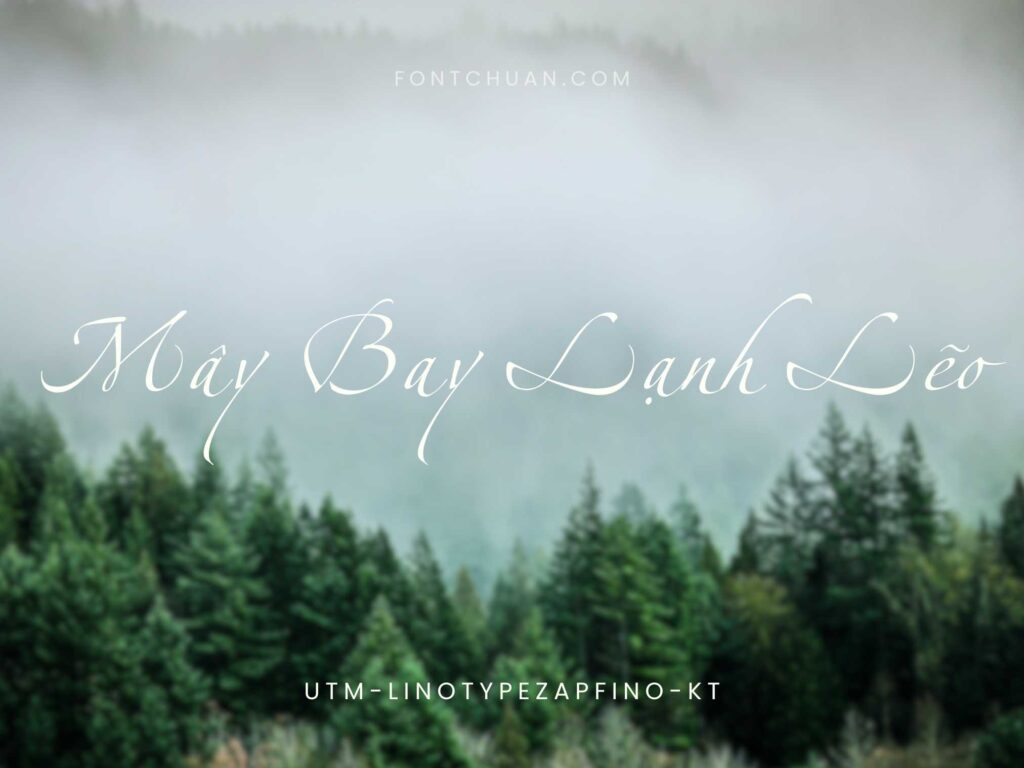
Font UTM Linotypezapfino Kt Việt Hóa
UTM LinotypeZapfino KT là một phông chữ thư pháp được thiết kế bởi Hermann Zapf và phát hành bởi Linotype vào năm 1998. Phông chữ này dựa trên bảng chữ cái mà Zapf đã viết tay vào năm 1944, thể hiện sự tinh tế và nghệ thuật trong từng nét chữ. Phông chữ đã được Việt hóa bởi Thiên Minh, hỗ trợ đầy đủ tiếng Việt cùng hơn 200 ngôn ngữ khác, giúp mở rộng khả năng sử dụng. Thành viên của Font Chuẩn đã sưu tầm và giới thiệu phông chữ này nhằm đáp ứng nhu cầu bạn đọc, cung cấp nguồn tham khảo chất lượng và ứng dụng thực tế vào các dự án thiết kế
Về đặc điểm thiết kế, UTM LinotypeZapfino KT có các đường nét uốn lượn mềm mại, độ tương phản cao và phong cách thư pháp đặc trưng. Phông chữ này phù hợp cho nhiều ứng dụng như thiết kế logo, tiêu đề, thiệp mời, biển hiệu và các dự án sáng tạo khác. Các ngành nghề như quảng cáo, ẩm thực, thiệp cưới và giáo dục có thể tận dụng phông chữ này để tạo nên sự khác biệt và thu hút trong các ấn phẩm thiết kế